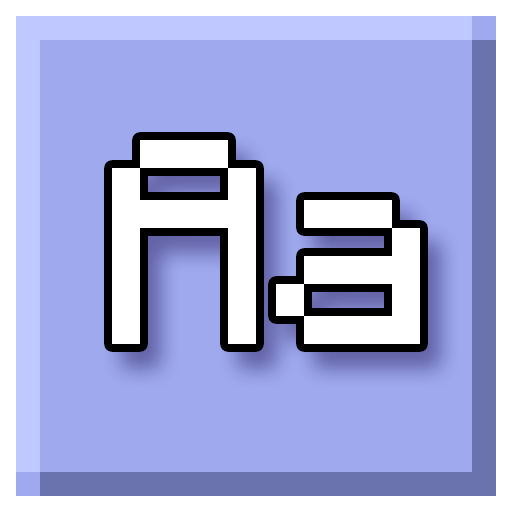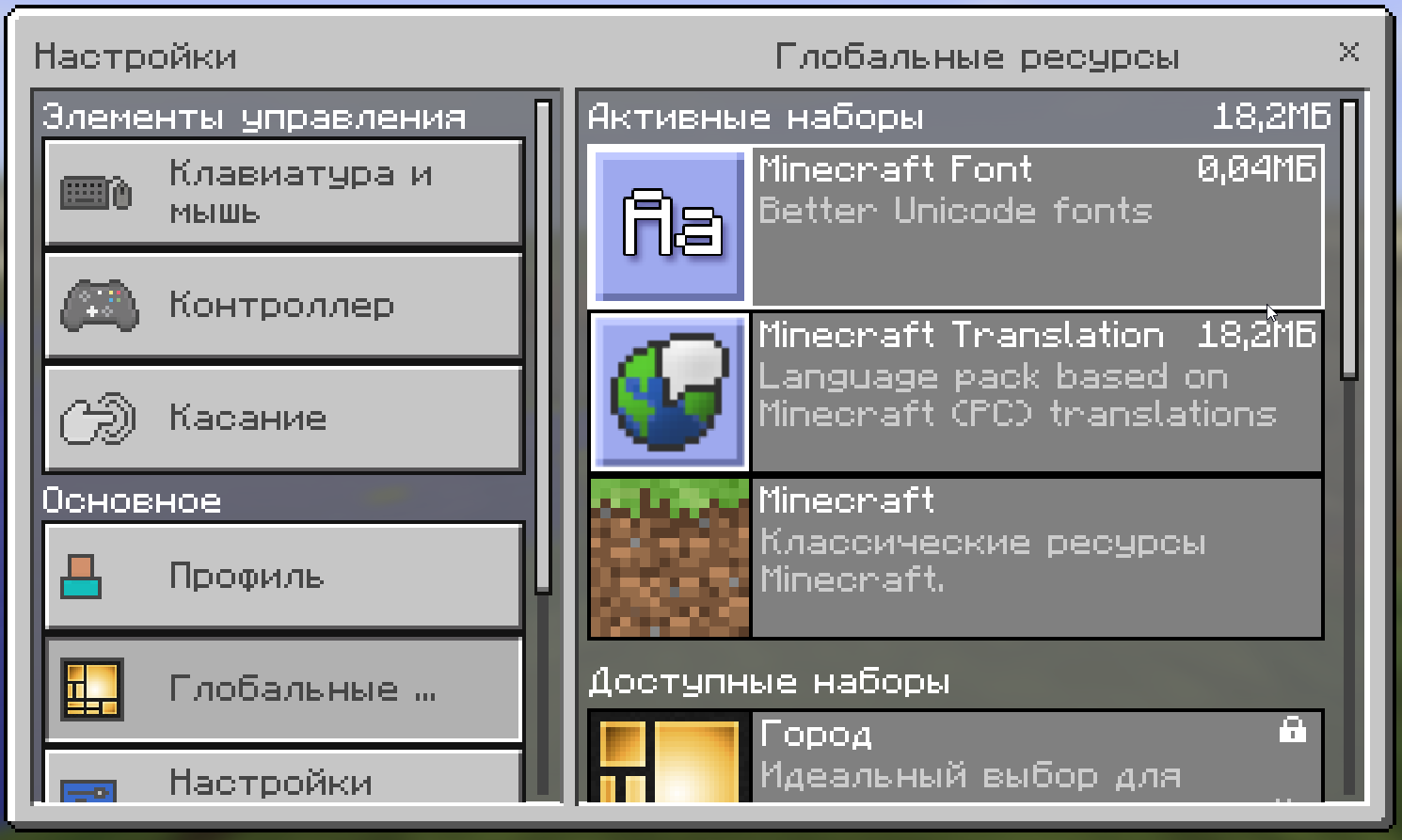
Minecraft Font Addon: Как изменить шрифт в Minecraft на более жирный
Если вам надоел стандартный тонкий шрифт в Minecraft, особенно при использовании кириллицы, то Minecraft Font Addon — отличное решение! Этот аддон заменяет дефолтный шрифт на более насыщенный и удобочитаемый. В этой статье разберём, как его установить и настроить для разных версий игры.
📌 Зачем менять шрифт в Minecraft?
Стандартный шрифт в Minecraft достаточно тонкий, что может вызывать дискомфорт при чтении, особенно в русской локализации. Minecraft Font Addon решает эту проблему, предлагая:
✅ Более чёткий и жирный шрифт – лучше читается в любых условиях.
✅ Поддержка кириллицы – русский текст выглядит аккуратнее.
✅ Совместимость с разными версиями – работает как в Minecraft PE (Bedrock), так и в Java Edition.
🔍 Примеры нового шрифта
Сравнение стандартного и нового шрифта:
- До:
Тонкий и не всегда разборчивый текст
- После:
Чёткий и удобочитаемый шрифт
Новый вариант особенно полезен в чатах, книгах и интерфейсах серверов.
⚙️ Особенности и совместимость
🔹 Работает с кириллицей, латиницей и другими языками.
🔹 Не влияет на производительность – это просто замена текстуры шрифта.
🔹 Можно комбинировать с другими ресурспаками, если они не изменяют шрифты.
Если вам важно, чтобы текст в Minecraft был удобочитаемым, Minecraft Font Addon — отличное решение. Простая установка, поддержка разных версий игры и улучшенная читаемость делают его полезным для всех игроков. Попробуйте и оцените разницу!